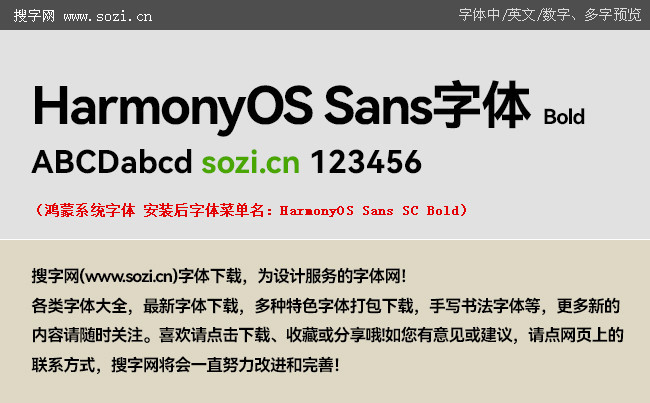
HarmonyOS-Sans字體(鴻蒙字體)-Bold
搜字網給大家提供一款HarmonyOS-Sans字體(鴻蒙字體)-Bold中文字體下載,HarmonyOS Sans字體是華為為HarmonyOS鴻蒙操作系統(tǒng)全新定制的系統(tǒng)默認字體。鴻蒙字體設計上聚焦于功能性、普適性,是一款多語言的無級可變字體。適合應用于藝術設計、平面宣傳設計、網頁設計等廣告設計。